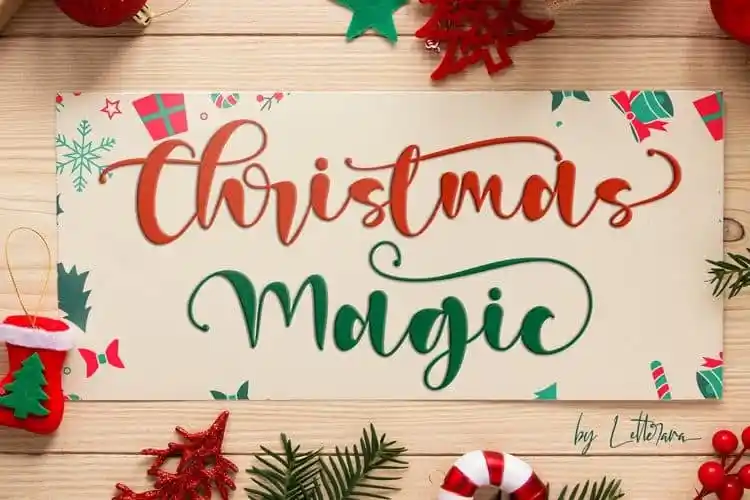
Christmas Magic Calligraphy Font – Fonte Grátis
Christmas Magic Calligraphy Font
A Christmas Magic Calligraphy Font é uma elegante tipografia script criada pelo Thomas Aradea, conhecido por suas alternativas círconflexuais e swashes perfeitos para desenhar com facilidade em programas como Silhouette. Esta fonte de PUA permite que você acesse todas as letras alternativas e swashes sem qualquer dificuldade. Com sua linha suave e traços variados, a Christmas Magic Calligraphy Font possui uma proposta visual fascinante e extremamente distinta, mantendo suas influências clássicas do calligráfico ao mesmo tempo que se mostra contemporânea e atual. Este é um belo exemplo de um tipo de letra de script que você pode usar para criar designs incrivelmente sólidos e eternos. Estamos certos de que você adorará sua aparência única, elegante e distinta. Faça dela uma parte importante em suas próximas criações visuais, especialmente se for destinadas a festas de Natal ou outros eventos onde um estilo mais elaborado é desejável.